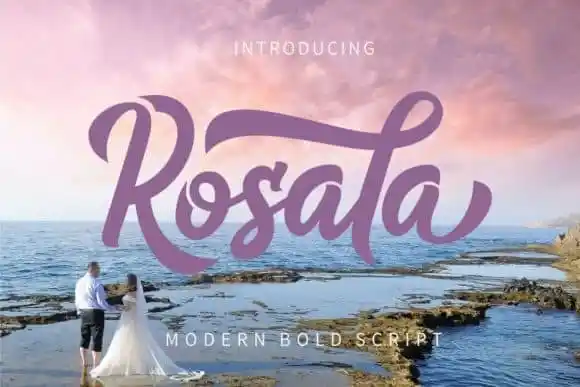
Rosala Script Font – Fonte Grátis
Rosala Script Font
A Rosala Script Font é uma tipografia feita à mão com estilo de escrita. Seu grosso e suave acabamento permite que esta fonte se adapte a uma variedade impressionante de ideias criativas, tornando-a versátil para muitos tipos de projetos. Desenvolvida pelo designer GFRcreative através do site 99designs, essa fonte é perfeita para estilos como logotipos e marca, fotografias, convites de casamento, cartões de papelaria, desenhos de casamentos e etiquetas. Suas linhas leves e elegantes garantem um toque personalizado em qualquer projeto que você escolha aplicá-la. Experimente a Rosala Script Font para dar um toque especial aos seus trabalhos gráficos.